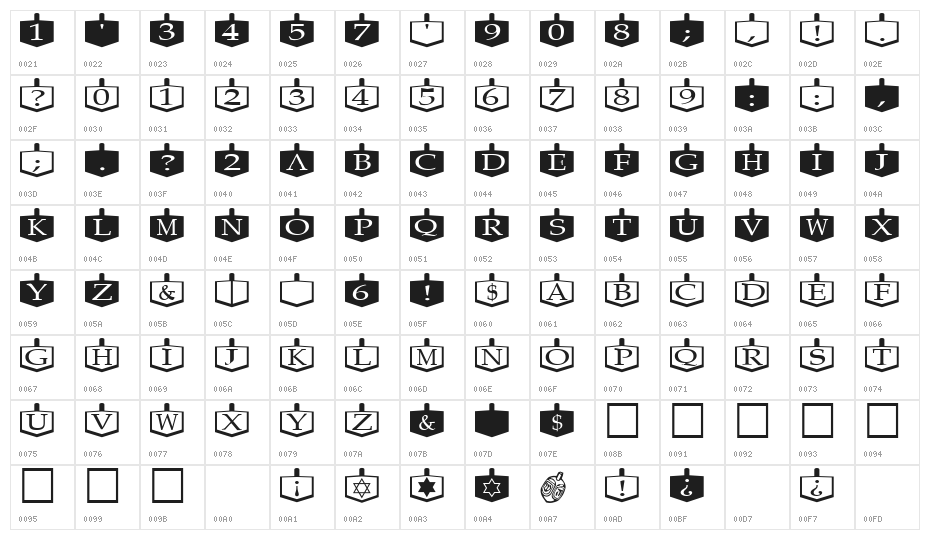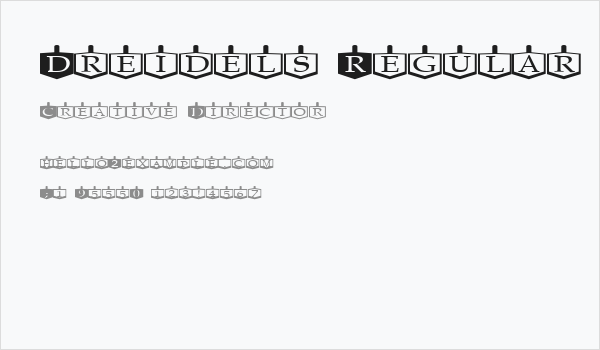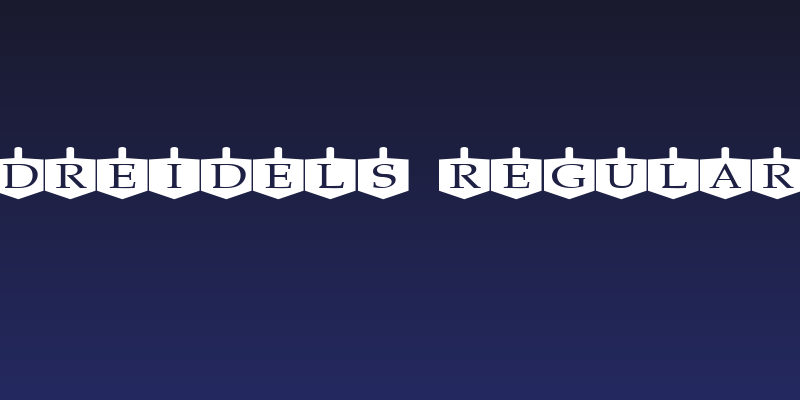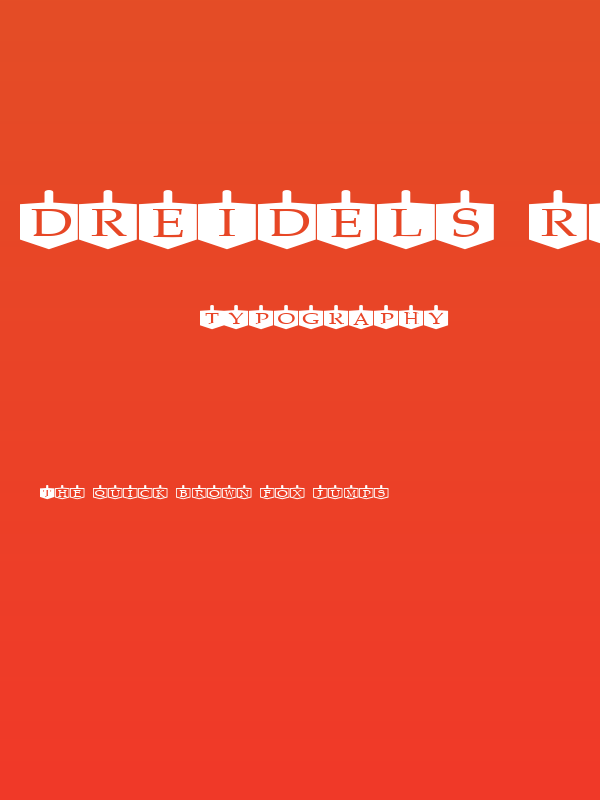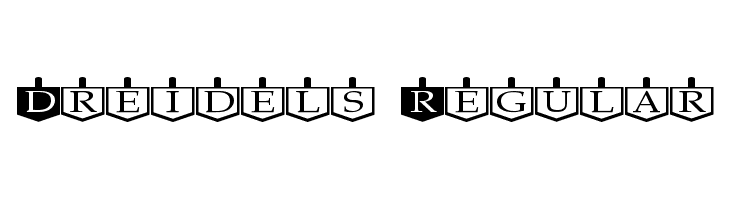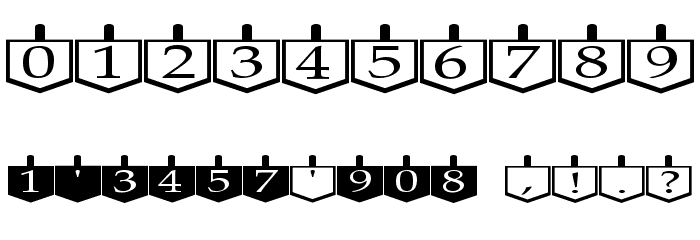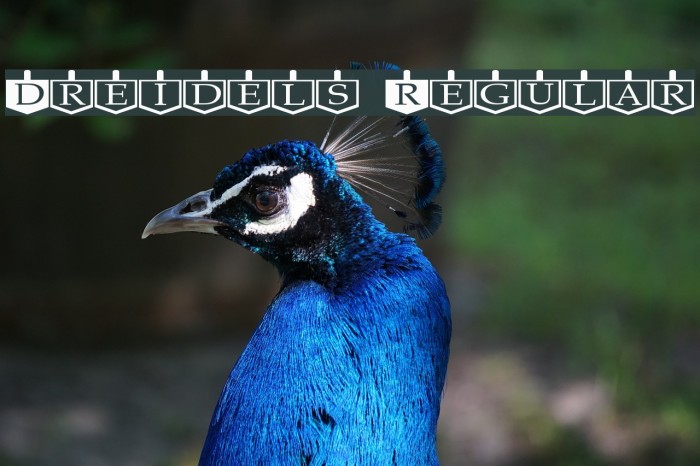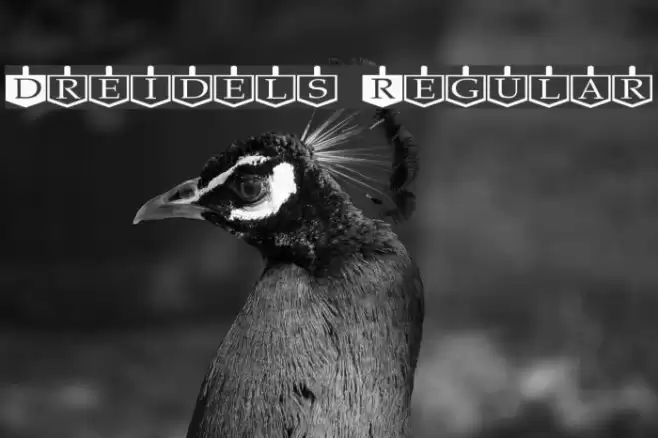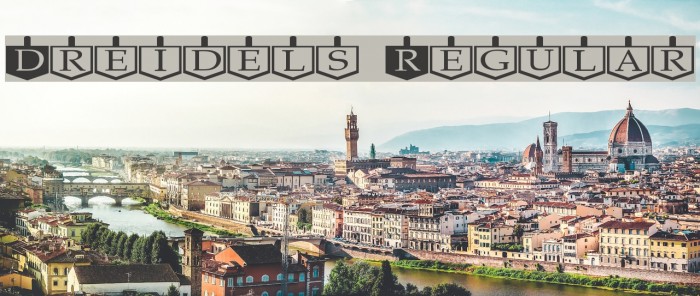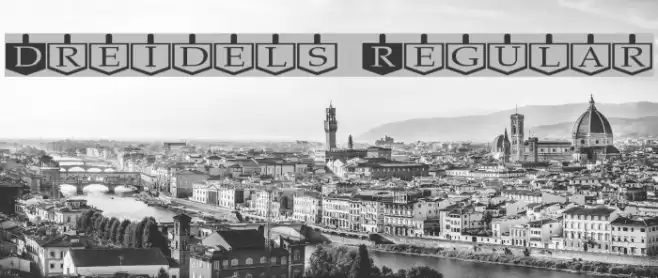
Dreidels Regular Font
| Caso d'uso | Headlines, Logos, Themed Invitations |
| Progetti proposti | Perfect for holiday cards, themed invitations, educational materials, or cultural event promotions. |